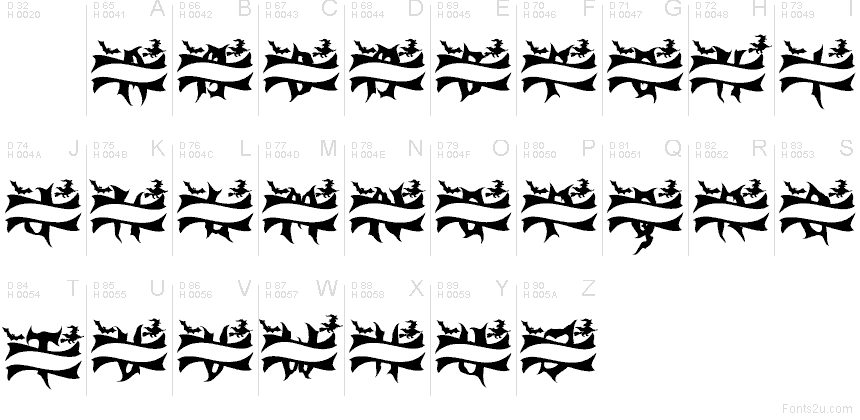
Dark Monogram
Dark Monogram de Yoga Letter es una tipografía gratuita de estilo monograma para Halloween, con una silueta ornamental y afilada creada a partir de murciélagos, una forma felina y una pequeña bruja sobre una escoba. Sus formas se curvan hasta terminar en puntas definidas, otorgándole al diseño un aire de fiesta espeluznante sin perder su ritmo decorativo.
Dark Monogram funciona de maravilla para invitaciones de Halloween, carteles de eventos, etiquetas para bolsas de dulces, páginas de scrapbook y gráficas estacionales en redes sociales. Esta fuente gratuita también es perfecta para iniciales decorativas, detalles en banners, pegatinas y proyectos temáticos de manualidades, ya que sus formas oscuras que se repiten se leen como un adorno de Halloween cohesionado en lugar de iconos separados.